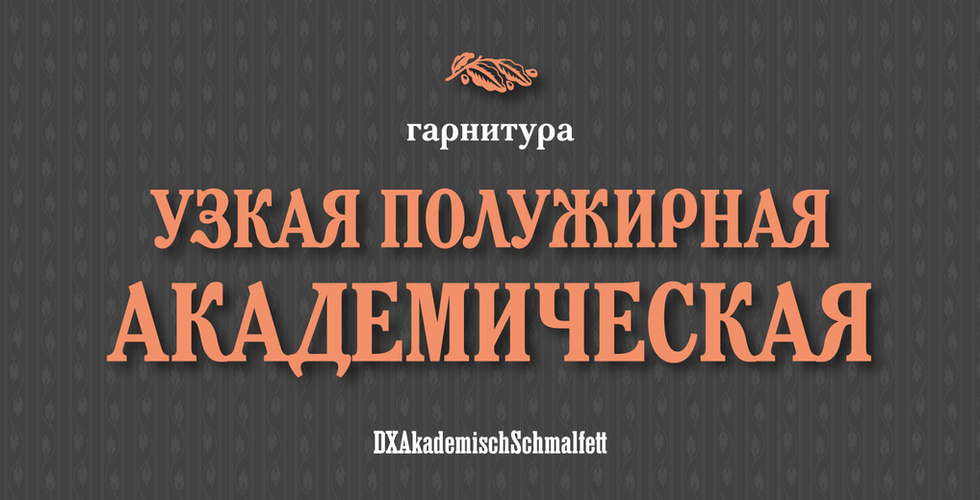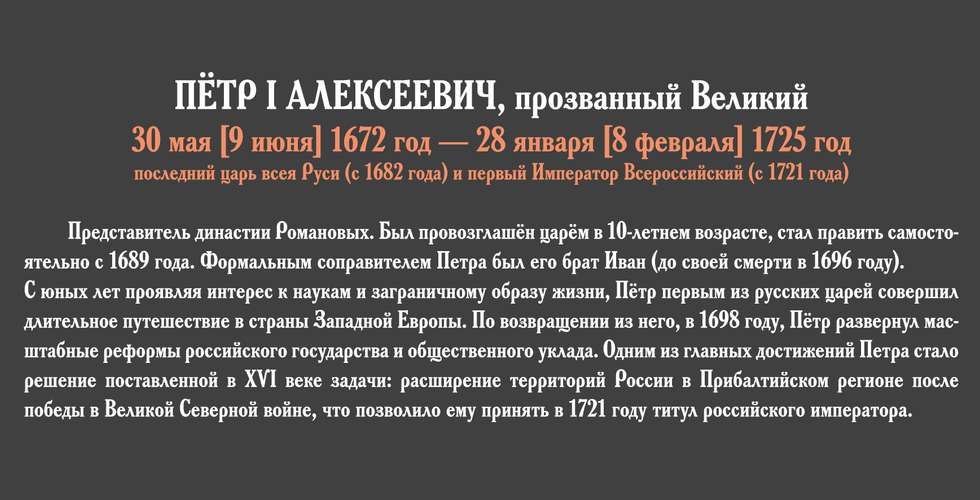
Шрифт Академический узкий полужирный/DXAkademischSchmalfett
Выпущен шрифт Академический узкий полужирный/DXAkademischSchmalfett.
Версия шрифта разработана на основе гарнитуры "Академическая узкая полужирная", словолитного заведения Г.Бертгольда (С.-Петербург). Словолитней за основу шрифта взято полужирное узкое начертание шрифта Sorbonne, 1905-08 (H. Berthold, Berlin), а разработанная кириллическая часть также имела характерные черты утверждённого Петром I гражданского шрифта.
Текстовый шрифт с небольшим контрастом между штрихами.
Для воссоздания использовались оттиски шрифта "Академический прямой жирный" из Каталога ручных и машинных шрифтов, Издательство Книга, 1966 г.; Каталога ручных шрифтов Харьковского шрифтолитейного завода, Прапор, 1973 г..
В отличии от оригинального исторического шрифта в данной версии кириллические знаки "Зз", "Рр", "Яя" и др. выполнены в общей стилистике гарнитуры DXAkademisch. Дополнительно в шрифте спроектированы цифры старого стиля, лигатуры, альтернативные и дополнительные знаки.